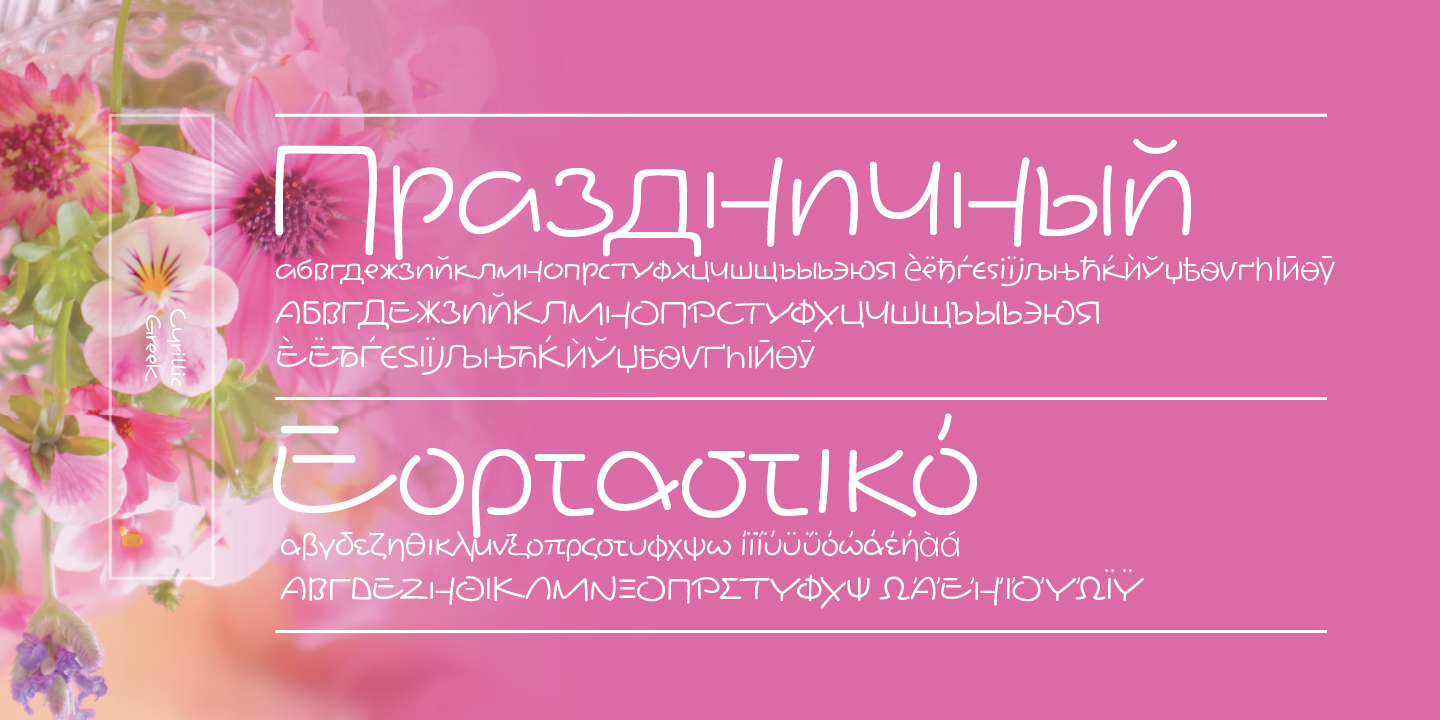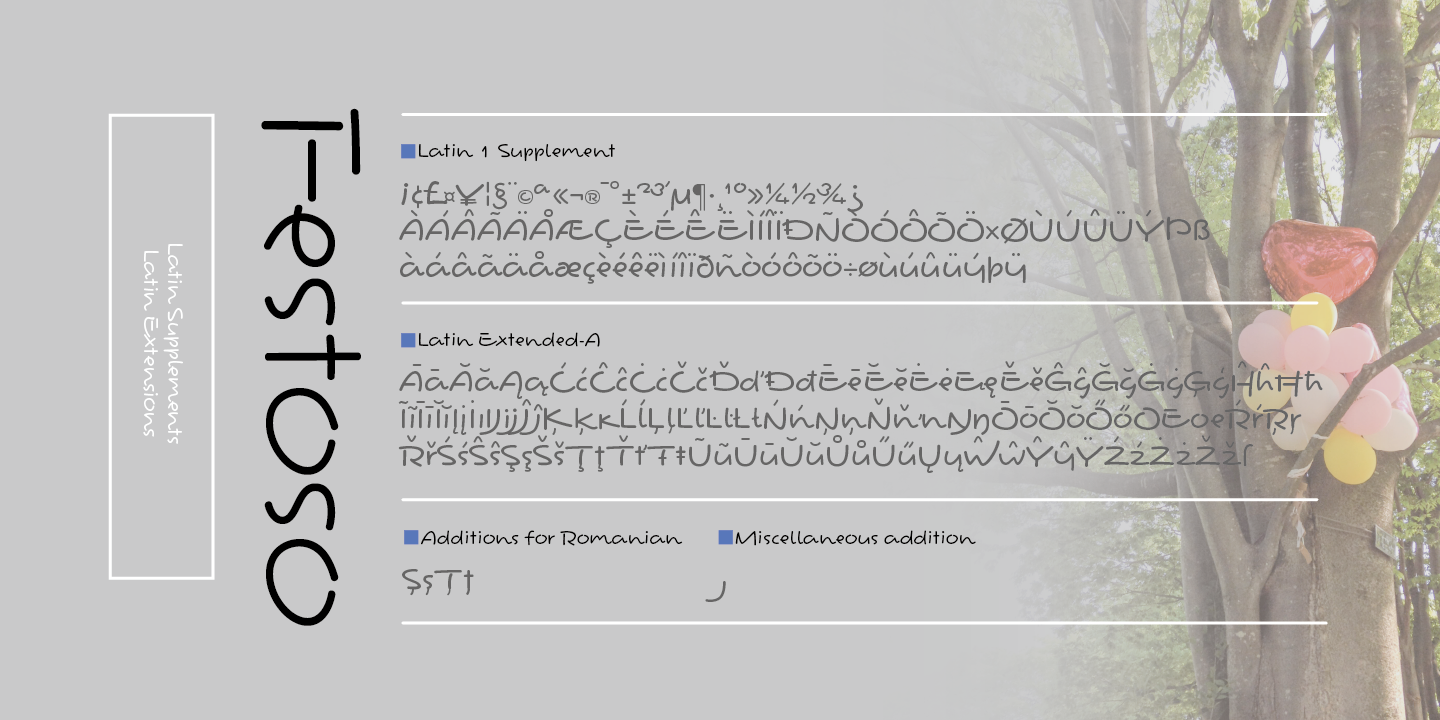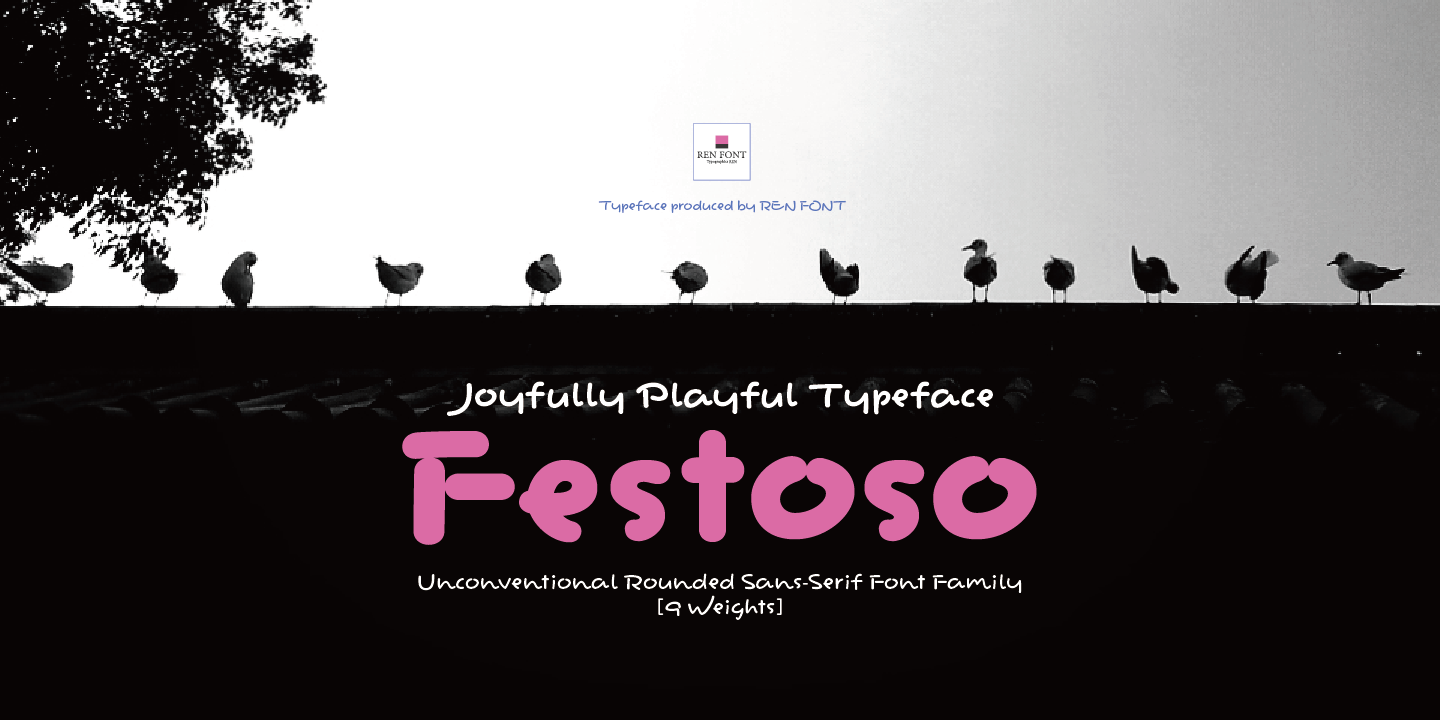
Festoso はイタリア語の音楽用語で、「陽気な」「楽しい」といった意味があります。音楽においては、演奏を陽気に、お祭りのように明るく行うよう指示する際に使われる表現です。
この書体 Festoso も、まさにそのお祭りのような陽気さを表現しています。跳ねる文字もあれば、ピタッと止まる文字もあり、予測不可能でバラエティに富んだ、リズム感あふれる破天荒なデザインです。使っているだけで気分が高まり、無条件に楽しくなってくるフォントです。
| 書体名 | ウエイト |
| Festoso | ExtraLight / Regular / Medium / Demibold / Bold / ExtraBold / Black / Heavy |